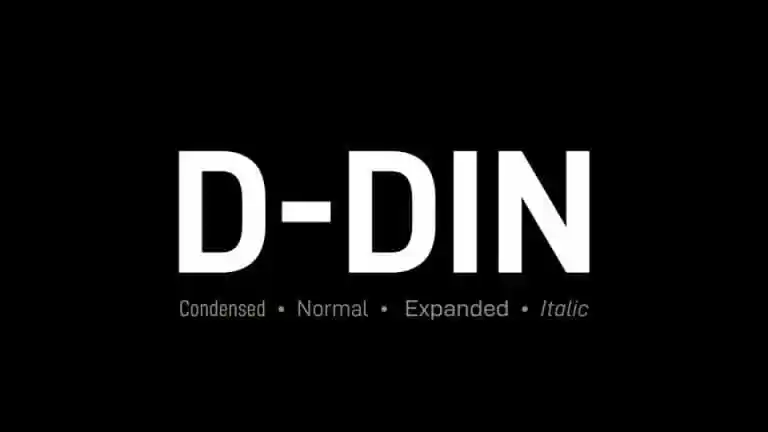
D-DIN Sans Serif Font Family – Download Grátis
A D-DIN Sans Serif Font é uma família de tipografias criada a partir dos formas geométricas básicas, fundamentadas no sistema de largura igual. Ela foi projetada e compartilhada pela Datto. Esta fonte se baseia na ideia original do tipo DIN, que era amplamente usada para aplicações como trânsito, administração e tecnologia. O DIN, a instituição germânica de padrões DIN – Deutsches Institut fur Normung (Instituto Alemão para Normalização), definiu estes tipos de fonte em seu documento DIN 1451-Schriften no ano de 1931. A D-DIN Sans Serif é uma tipografia de face nesses moldes, sendo uma família que segue o design do famoso tipo DIN. Através deste projeto, a Datto oferece um conjunto de fontes perfeitas para designers e criadores digitais em busca de um estilo moderno e funcional sem as serifas tradicionais. Suas formas geométricas puras e seu equilíbrio na distribuição da largura de letras tornam-a uma escolha versátil e eficaz para qualquer projeto que valorize uma aparência limpa e elegante, desde materiais de comunicação até interface de dispositivos digitais.